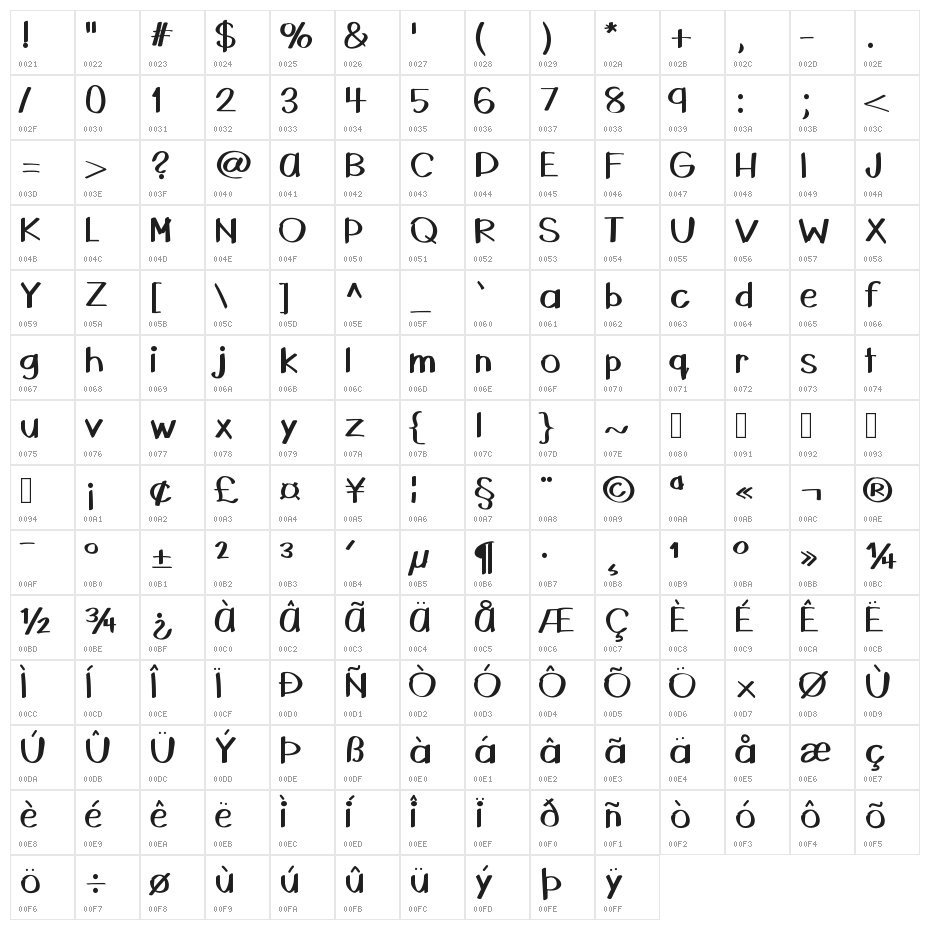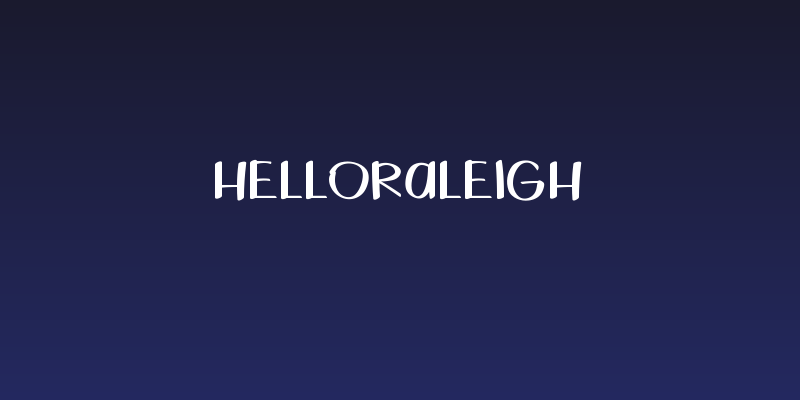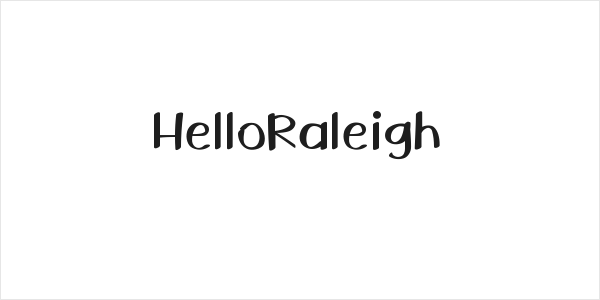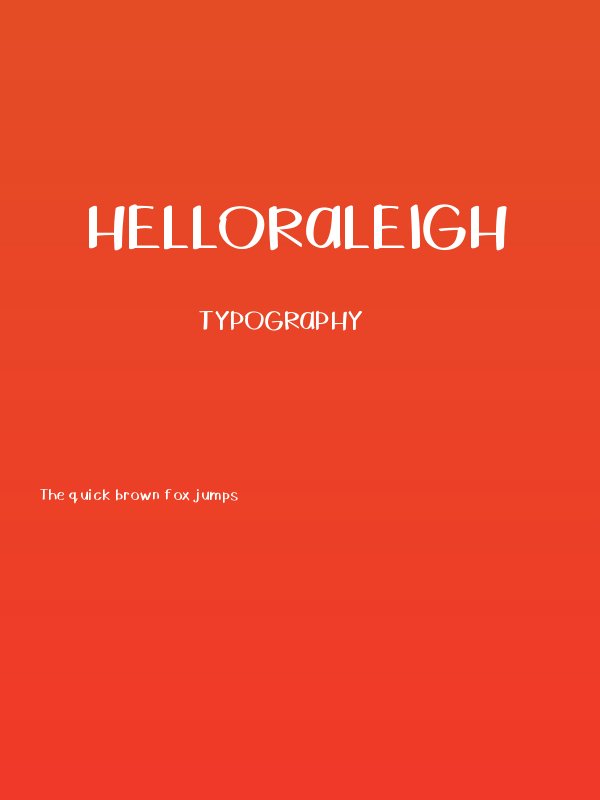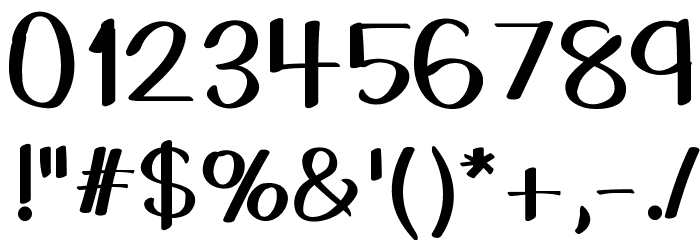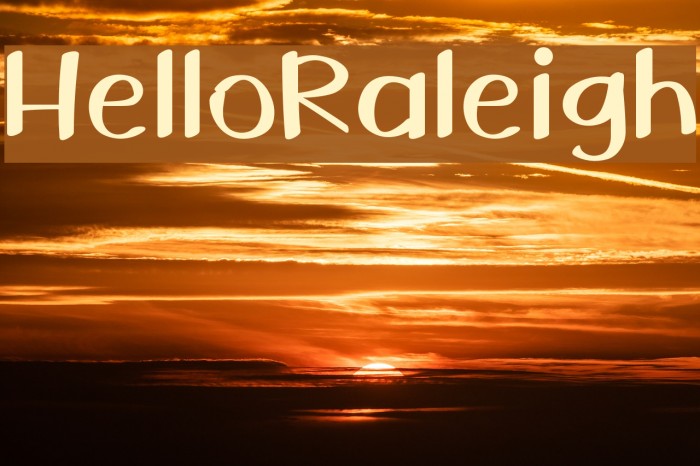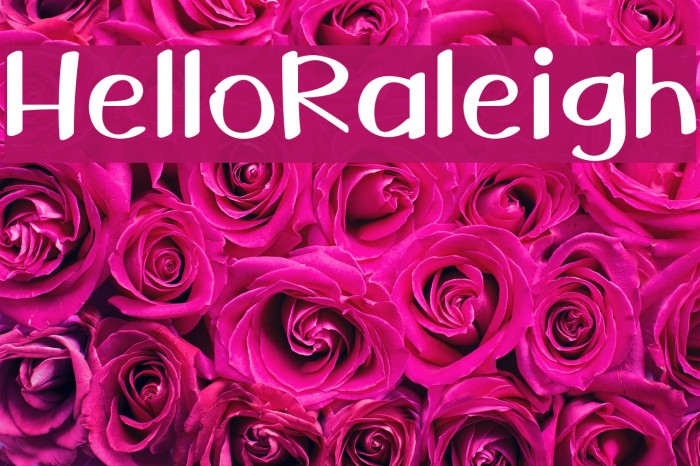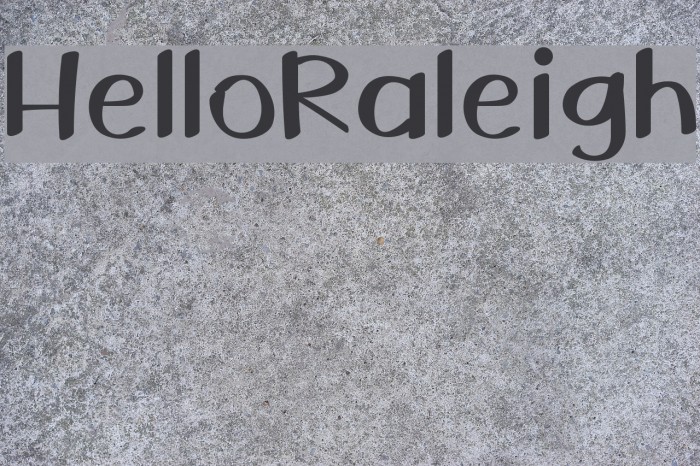
HelloRaleigh Font
| Estilo general | Playful |
| Caso de uso | Headlines, Logos, Informal Text |
| Proyectos propuestos | Perfect for children's books, greeting cards, playful branding, and social media graphics. |